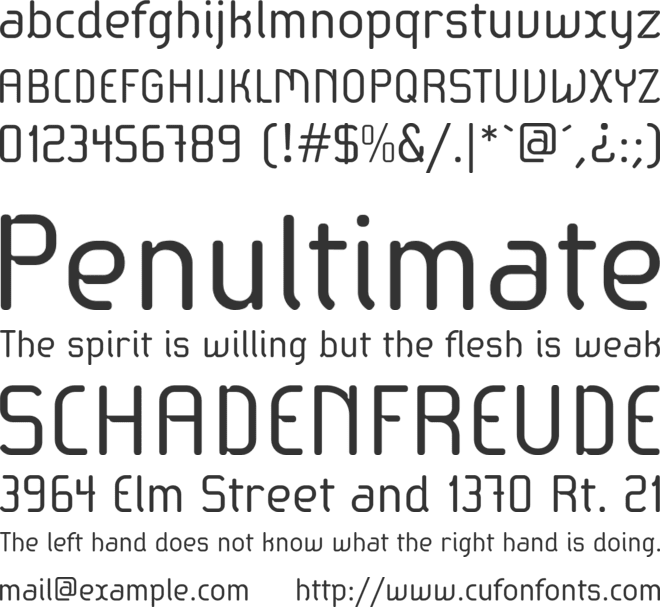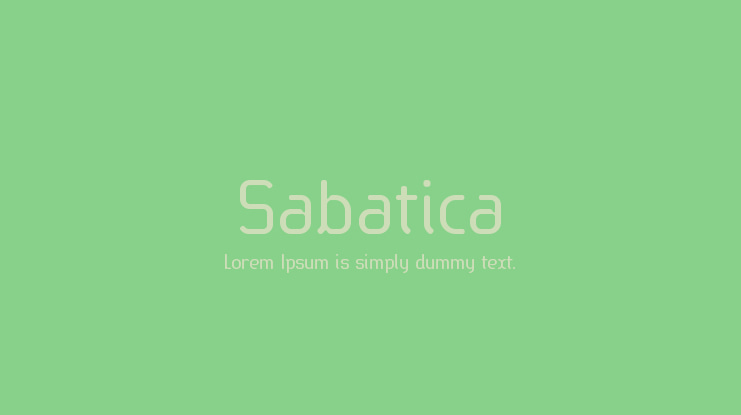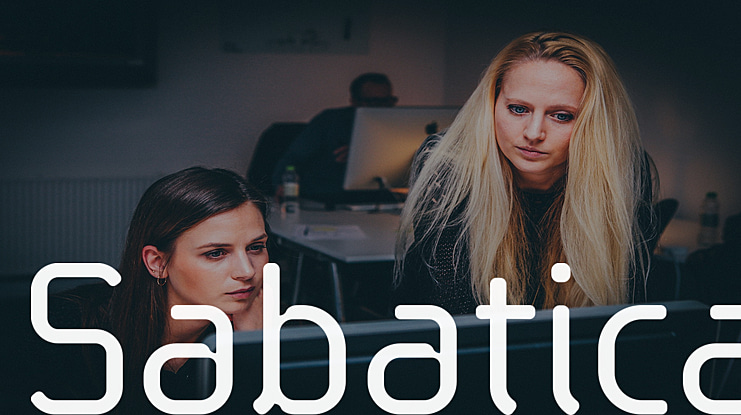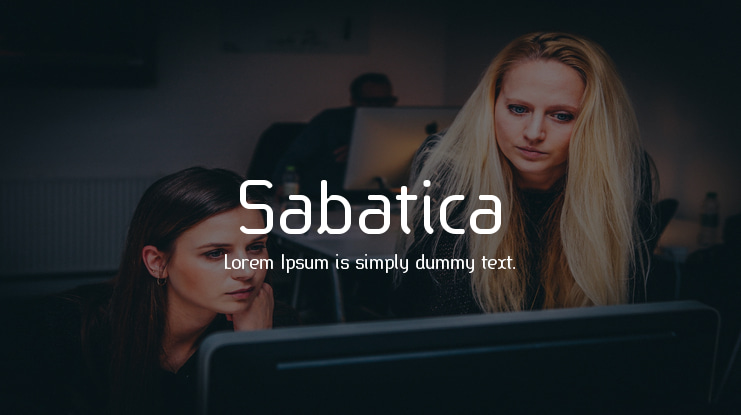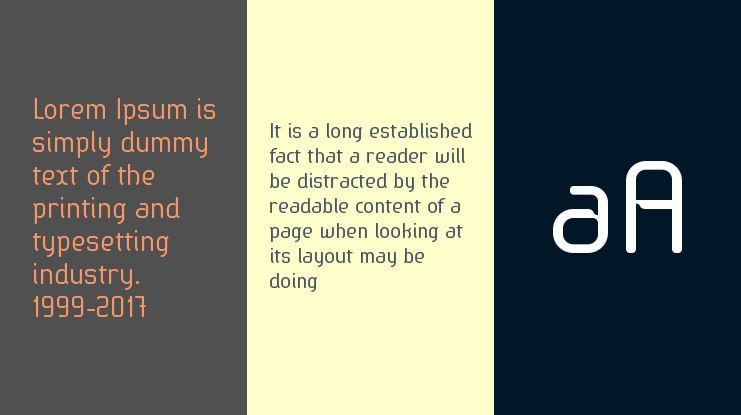
Sabatica Font
deFharo
Una tipografía sabática, por que la comencé a diseñar un sábado sin nada mejor que hacer. A Sabbath font, for that I started designing a Saturday with nothing better to do.